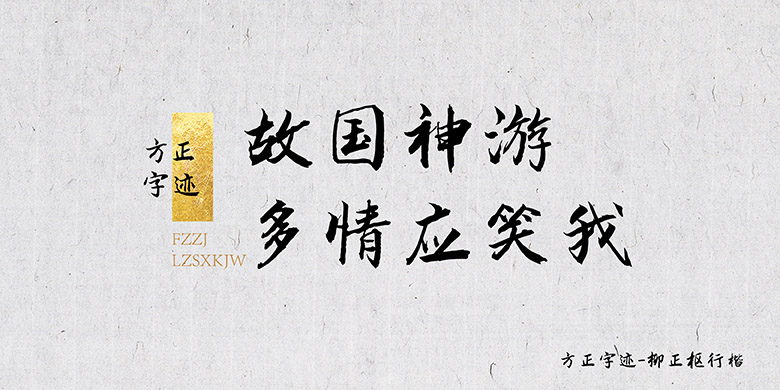
方正字迹-柳正枢行楷
该款字是柳正枢先生将唐代颜、褚、虞、欧、柳等楷书字体与王羲之行书糅合之后形成的行楷书字体,兼具楷书的工整与行书的柔美,章法流畅,苍劲有力。柳正枢先生在字体创作过程中,在保持字迹清晰工整的前提下,通过不断总结与变化,最大程度展现了汉字艺术的美学,赋予了该字体正、精、实的审美标准,是书法家在新时代向中国汉字传统文化的致敬。